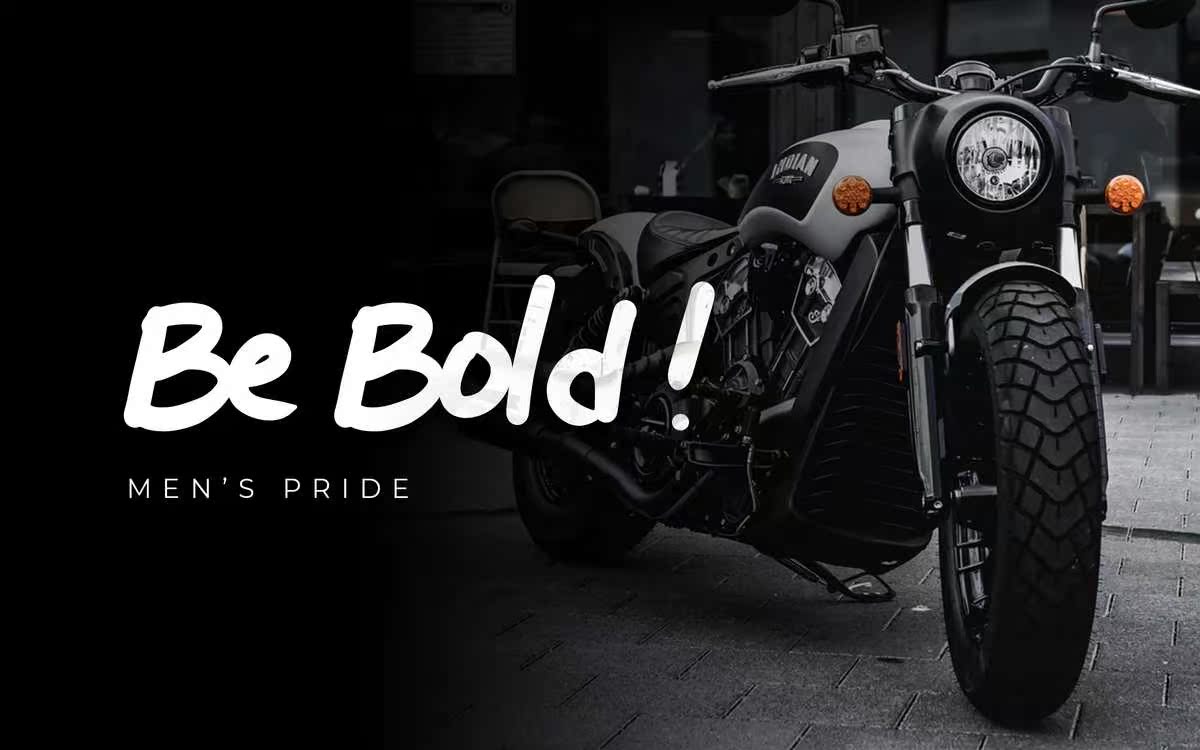
HellofGerisa Causure and Laxed HandwittenFont。它的甜美和充满活力的样式使此Fontaw在您的设计中得到了完美的选择。HellofGerisa Causure and Laxed HandwittenFont。它的甜美和充满活力的样式使此Fontaw在您的设计中得到了完美的选择。